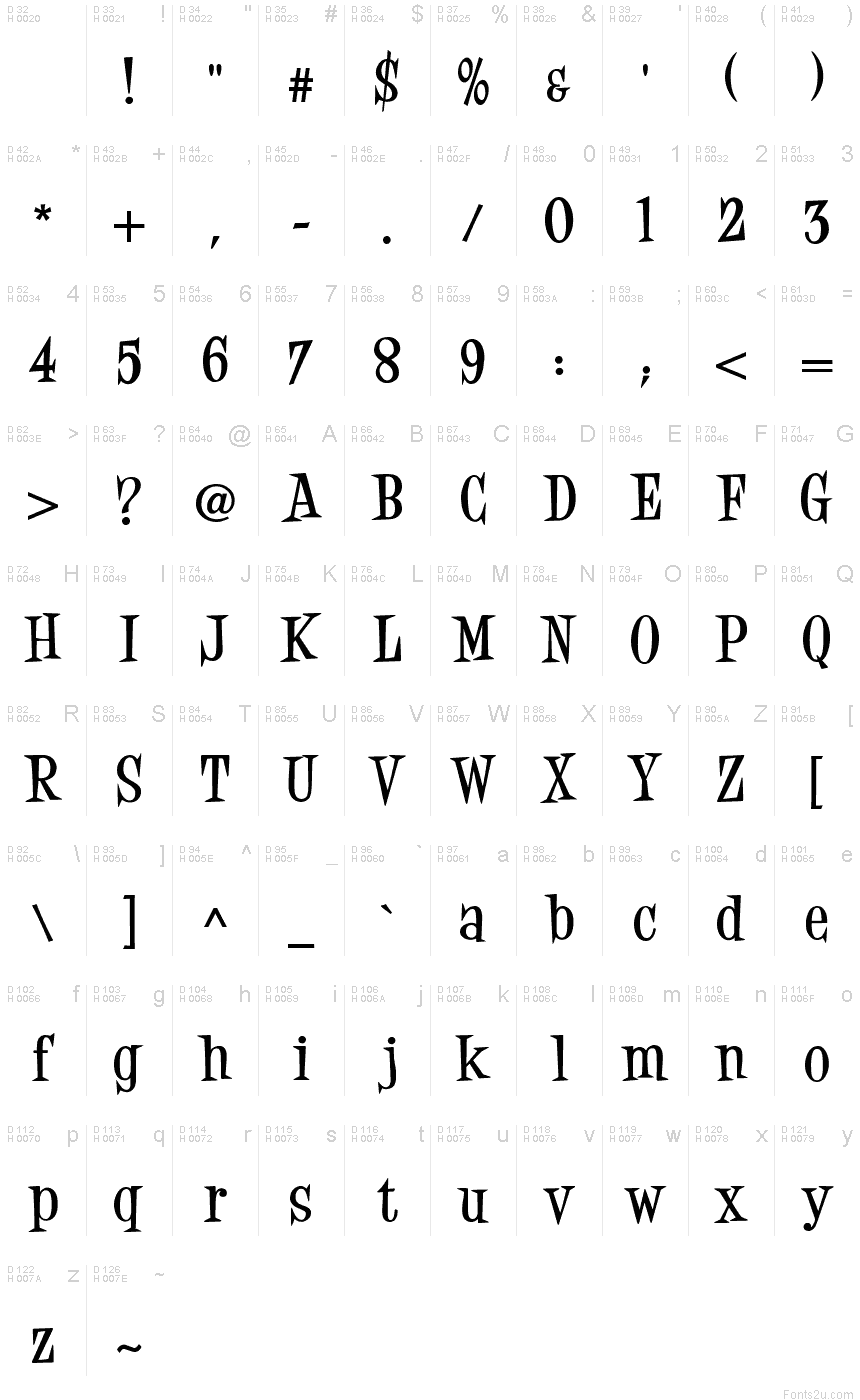
Desigers Bold to darmowy krój szeryfowy o wysokiej, smukłej sylwetce i lekko teatralnym rytmie, który sprawia wrażenie eleganckiego, a nie formalnego. Ostre krzywizny i wydłużone proporcje nadają nagłówkom szlachetny, vintage’owy charakter, dzięki czemu świetnie sprawdza się na okładkach książek, w identyfikacji butików, na plakatach, w nagłówkach magazynów, menu czy opakowaniach.
Desigers Bold sprawdza się wszędzie tam, gdzie potrzebujesz czegoś dekoracyjnego, ale wciąż czytelnego na pierwszy rzut oka. Ten darmowy font dodaje wyrafinowanego, klasycznego klimatu logotypom, zaproszeniom, łamom redakcyjnym i szyldom, zwłaszcza w zestawieniu ze spokojnym, neutralnym krojem bezszeryfowym w tekście uzupełniającym.